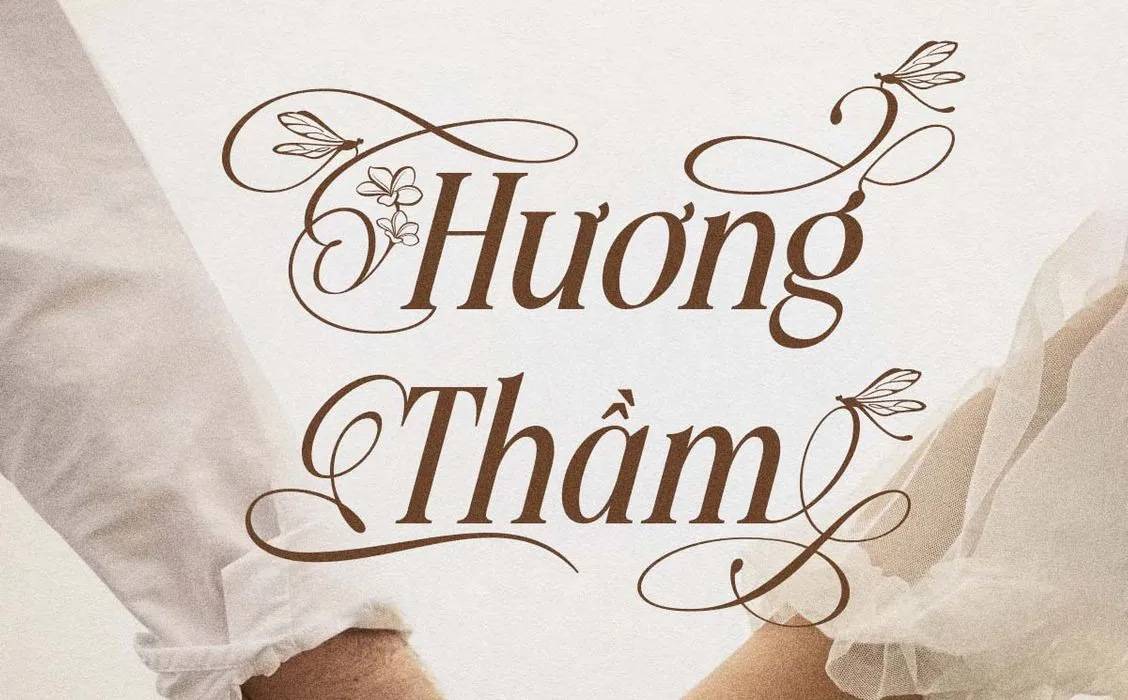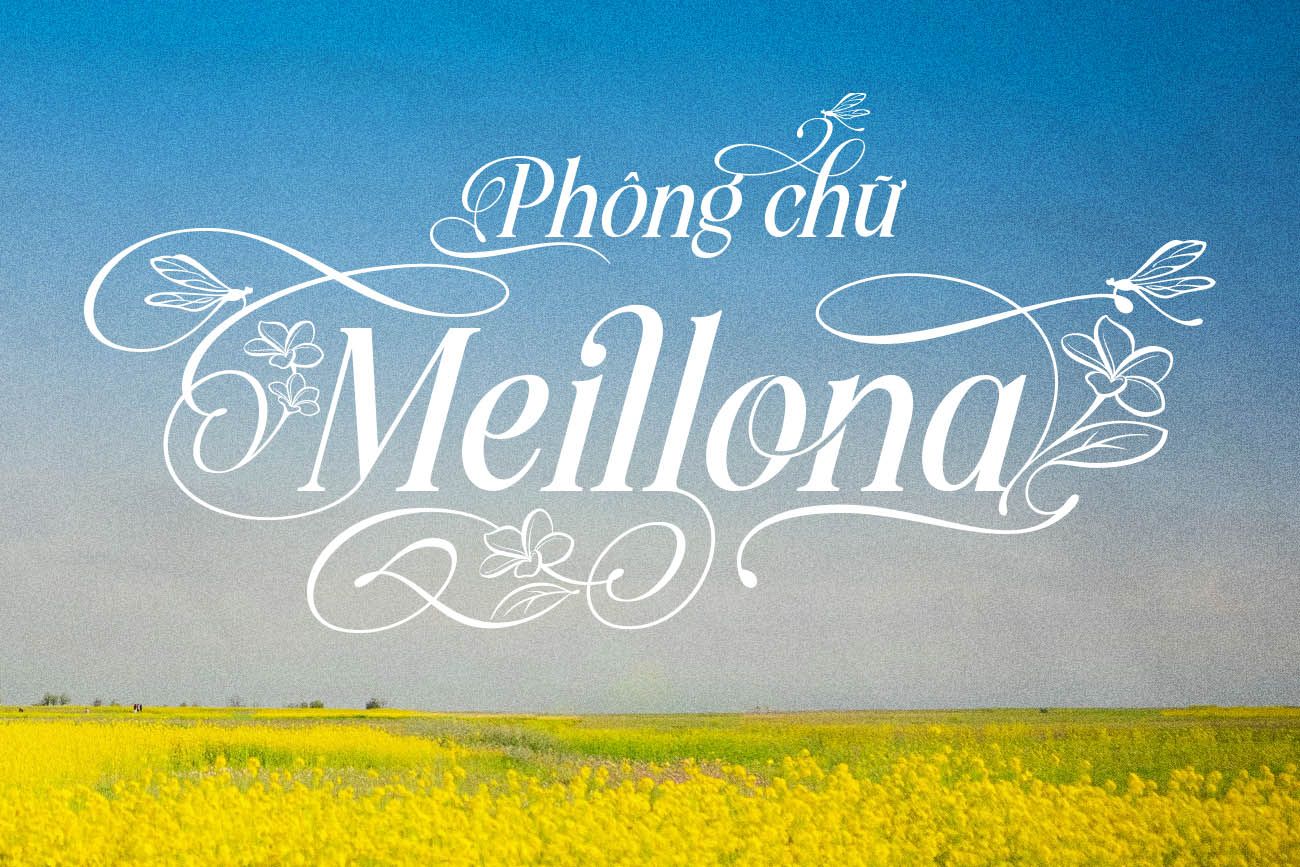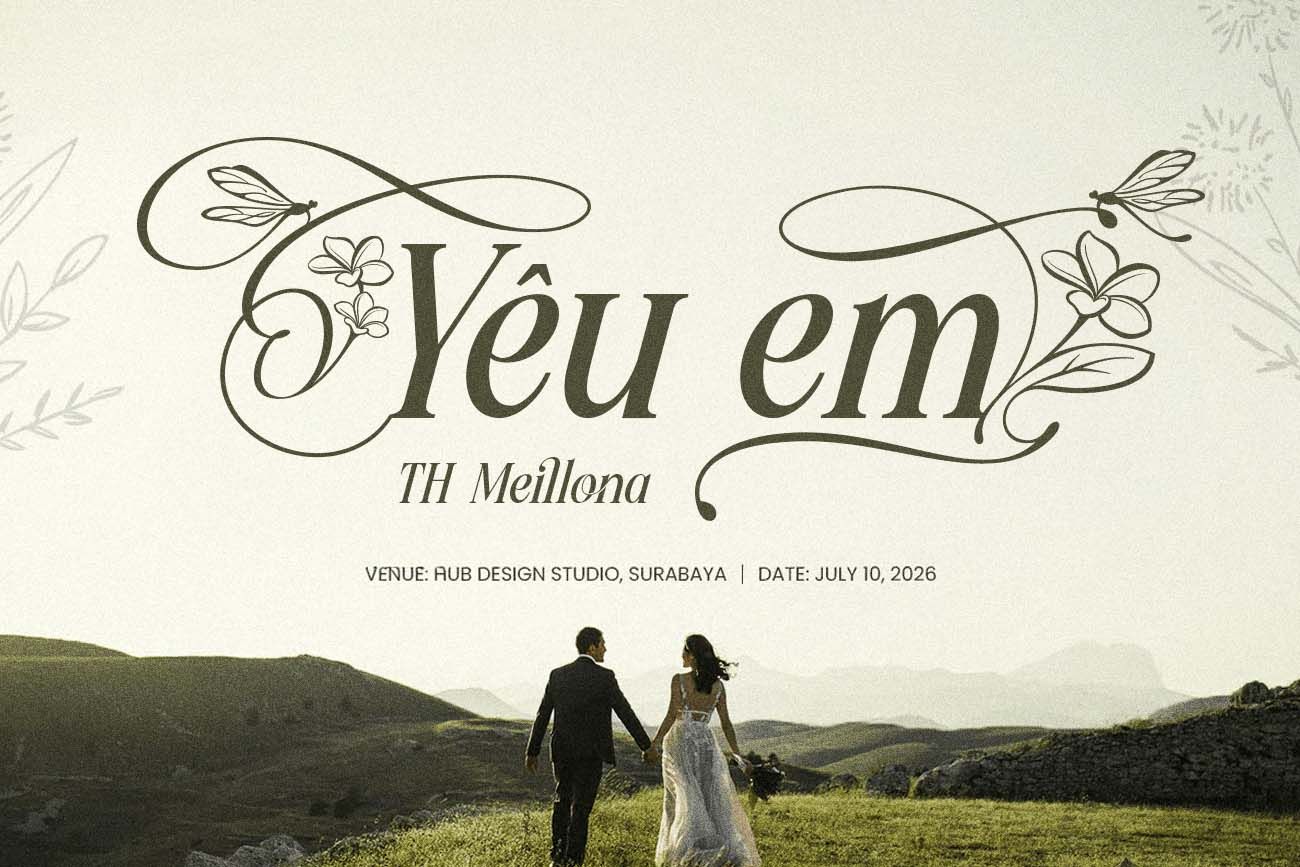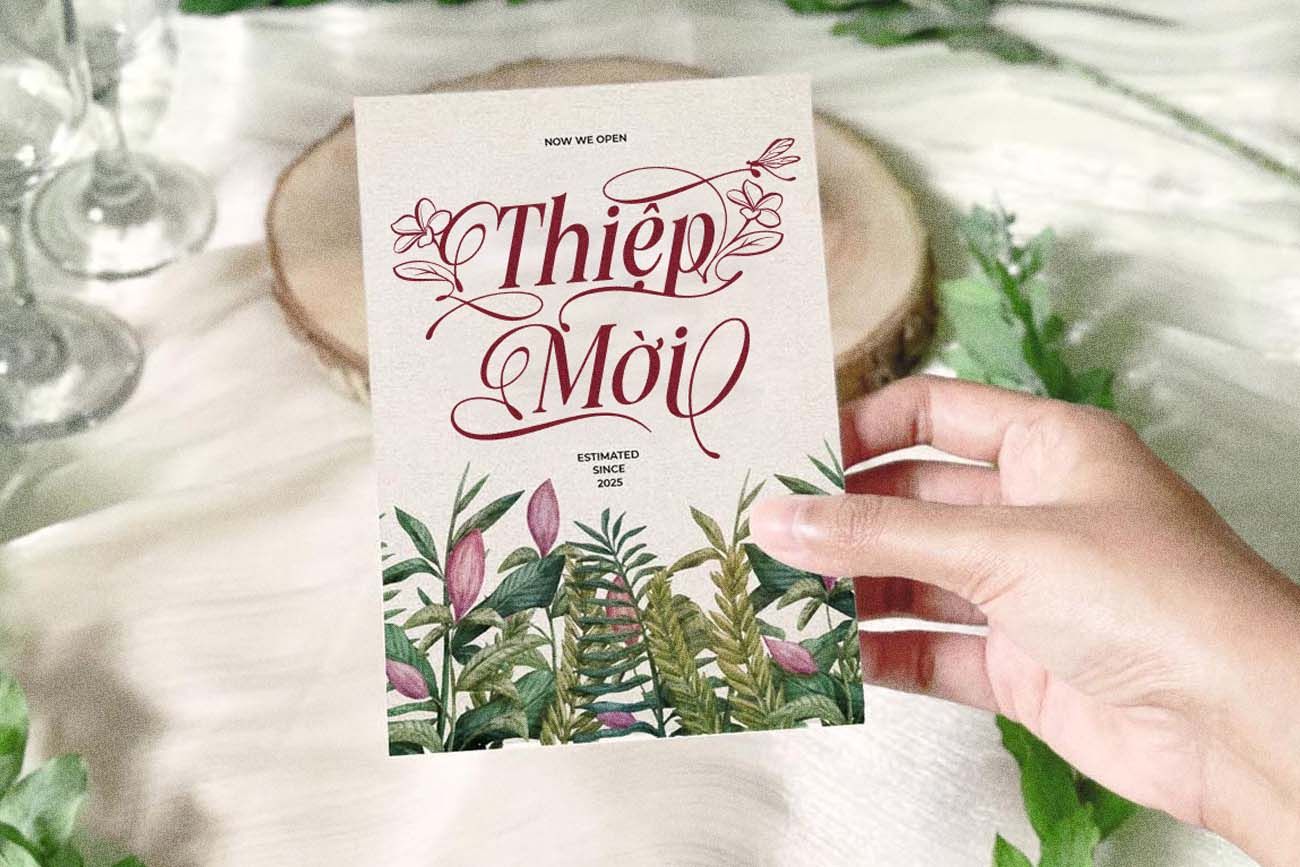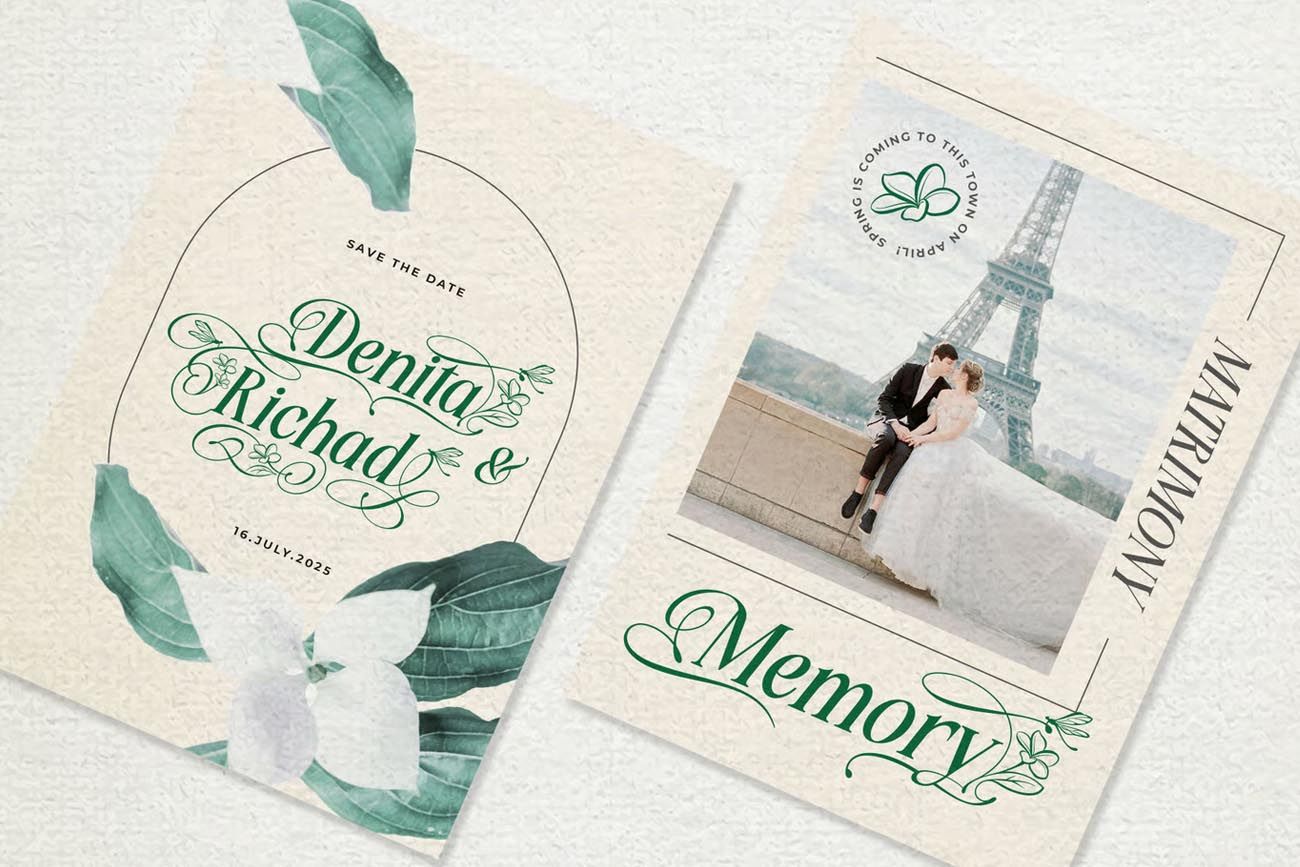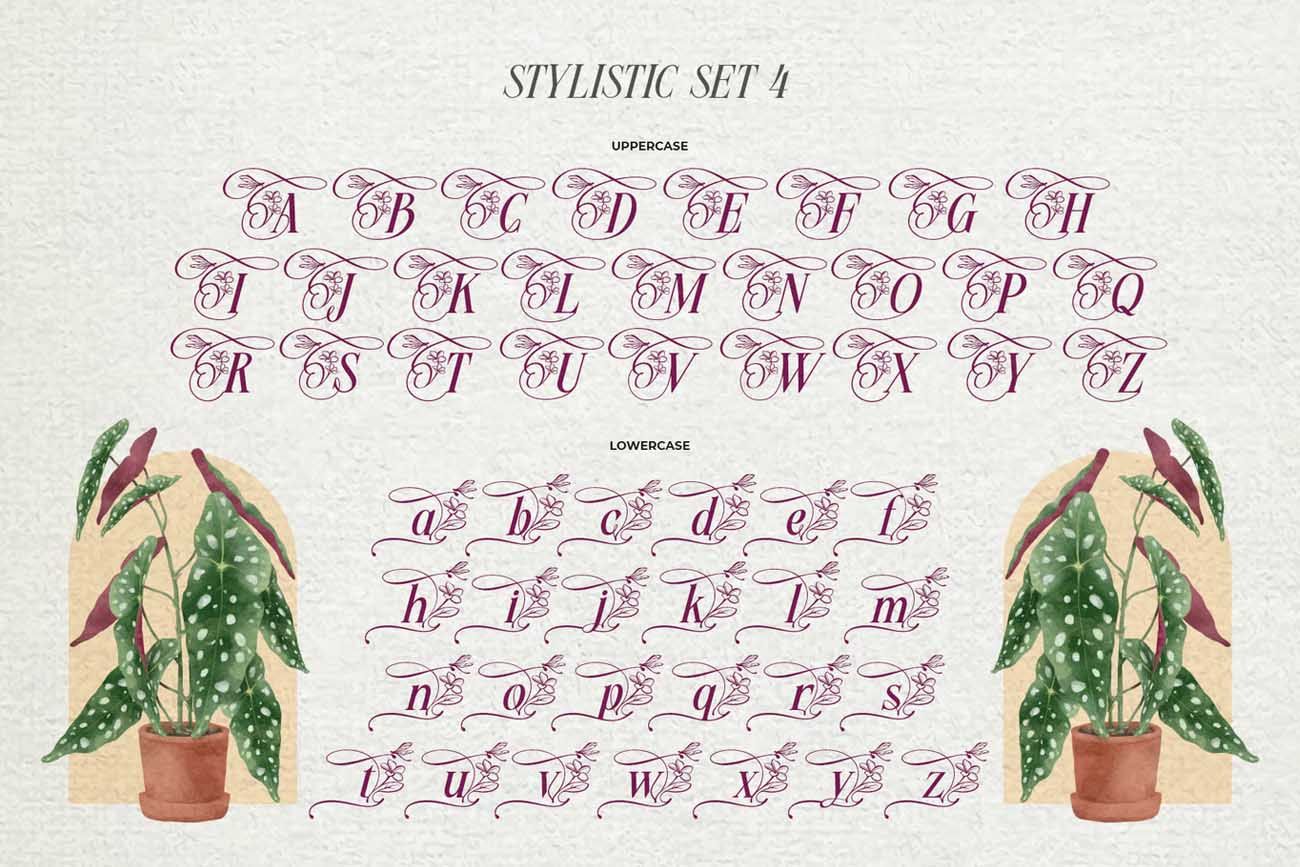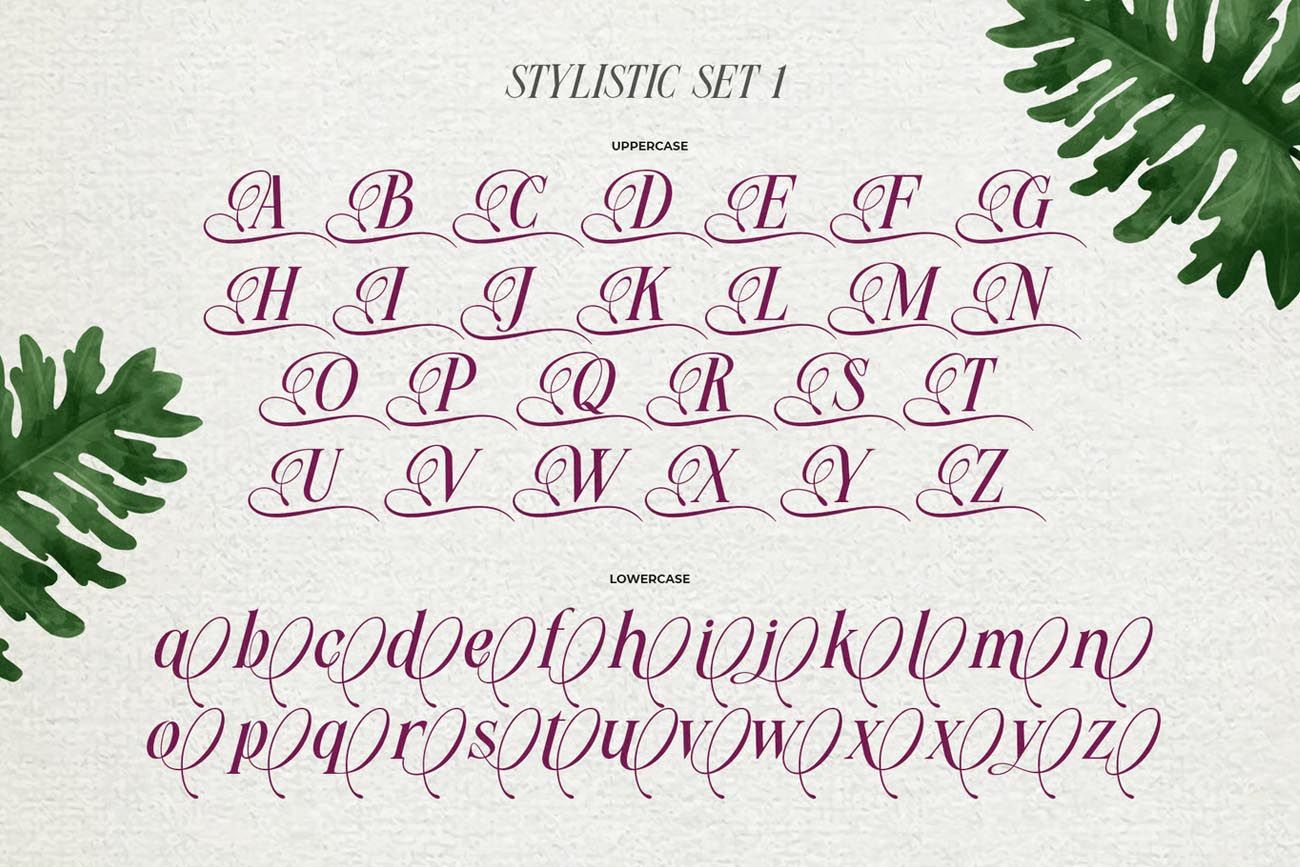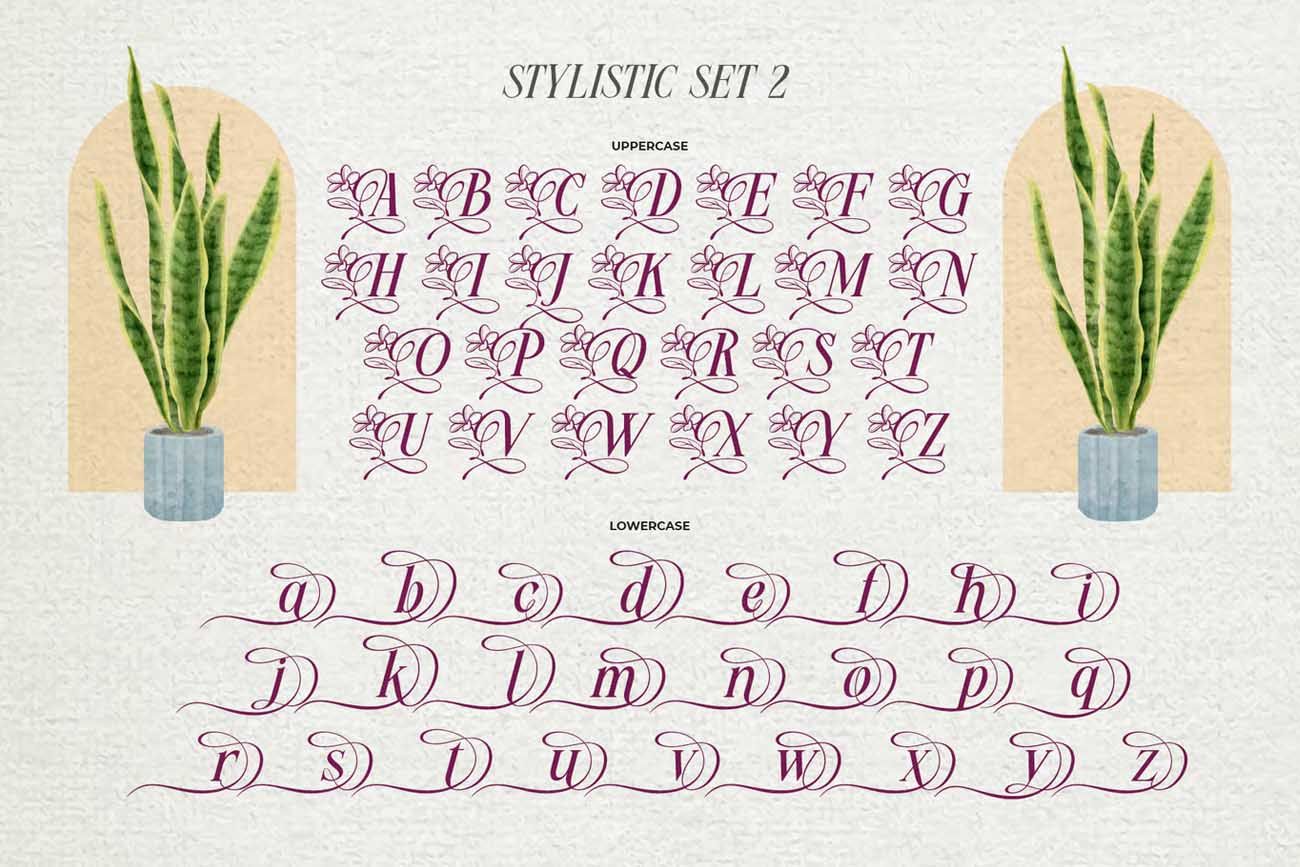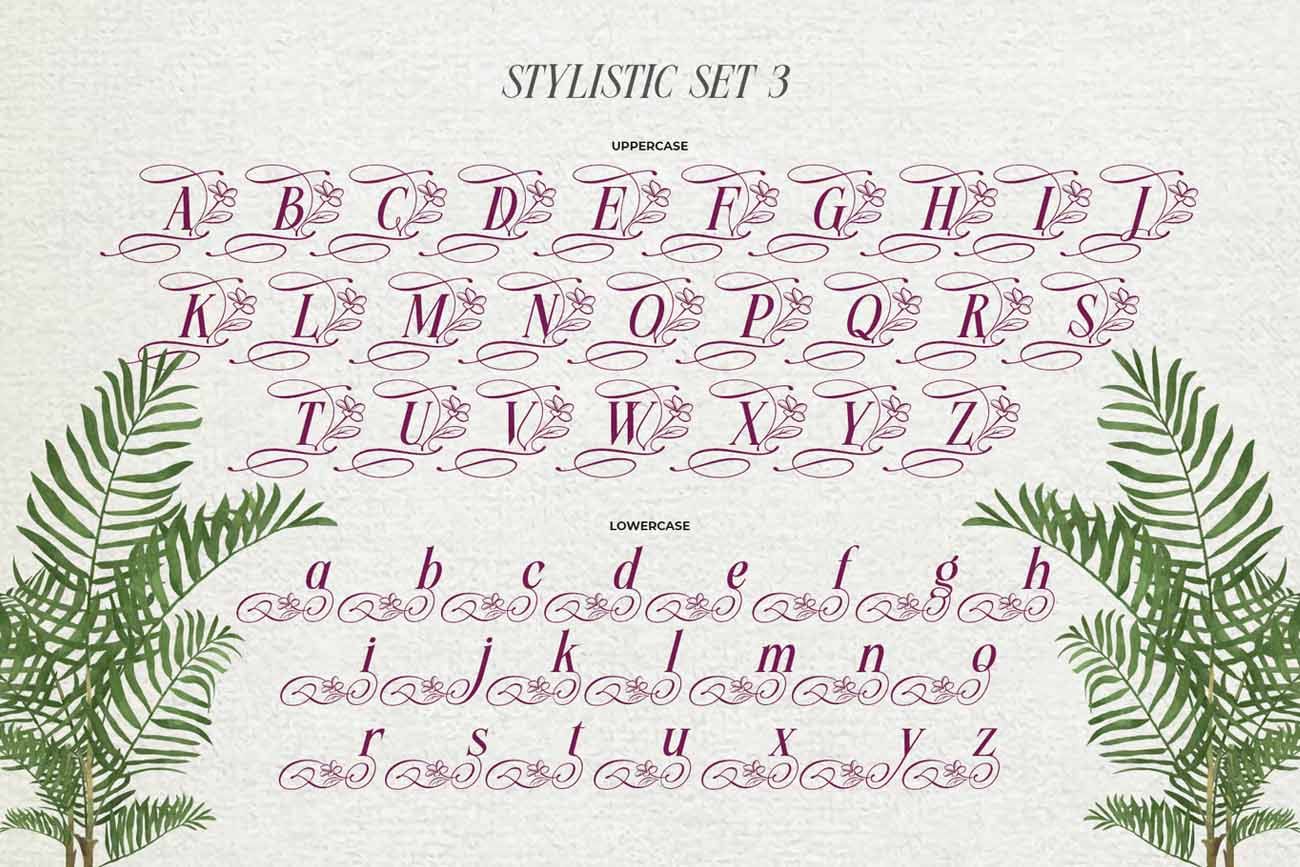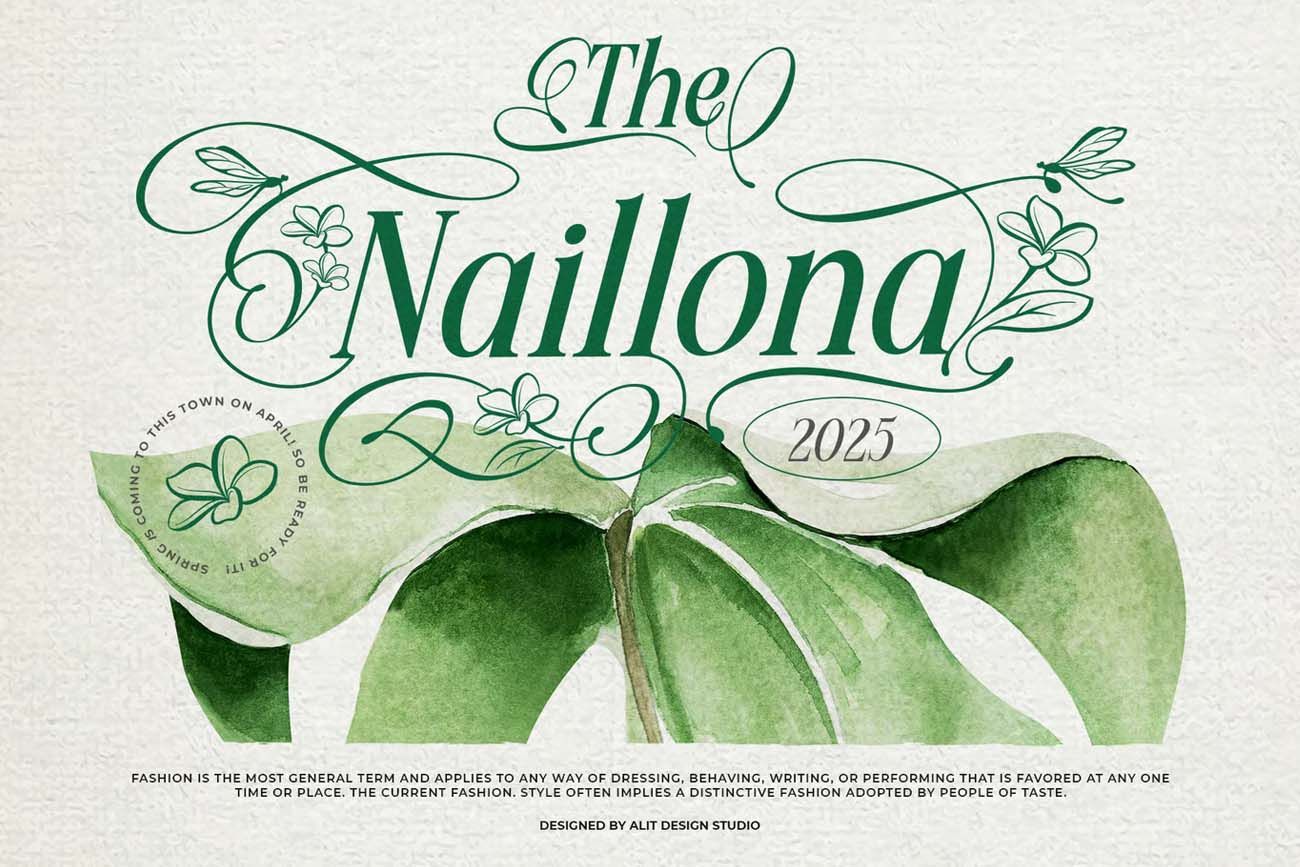
Trong thế giới thiết kế, một font chữ đẹp không chỉ đơn thuần là công cụ trình bày mà còn là “linh hồn” giúp truyền tải cảm xúc. Font chữ TH Meillona Việt hóa là một lựa chọn hoàn hảo dành cho những ai yêu thích sự lãng mạn, mềm mại nhưng vẫn sang trọng. Với những đường nét bay bổng, hoa văn tinh xảo, phông chữ này mang lại cảm giác nghệ thuật và phù hợp với nhiều phong cách sáng tạo khác nhau.
TH Meillona được phát triển từ font gốc Meillona, một sản phẩm nổi bật của Typetemp Studio, vốn nổi tiếng với nhiều thiết kế font chữ nghệ thuật. Phiên bản Việt hóa do Phạm Sơn thực hiện đã được tối ưu đầy đủ dấu tiếng Việt, chỉnh sửa kerning và giữ nguyên những chi tiết hoa lá mềm mại, đảm bảo người dùng có thể áp dụng dễ dàng trong nhiều dự án thiết kế mà không gặp lỗi ký tự. Đây chính là điểm cộng lớn giúp TH Meillona nhanh chóng được cộng đồng designer Việt Nam đón nhận.
Đặc điểm nổi bật của phông chữ TH Meillona Việt hóa là hệ thống stylistic alternates đa dạng, với hàng trăm glyphs, chữ hoa – chữ thường đều có thể biến hóa thành nhiều kiểu dáng khác nhau. Các đường flourishes mềm mại đi kèm họa tiết hoa lá, cánh bướm, mang đến sự uyển chuyển đầy nghệ thuật. Chính vì vậy, font chữ này đặc biệt phù hợp cho các dự án mang tính cá nhân hóa và cần sự sáng trọng, ví dụ như thiệp mời cưới, poster lãng mạn, typography nghệ thuật hay bộ nhận diện thương hiệu cao cấp.
Một điểm nổi bật khác chính là tính ứng dụng. Không chỉ gói gọn trong thiết kế thiệp cưới, TH Meillona Việt hóa còn có thể được sử dụng trong các dự án thiết kế logo, tiêu đề sách, bìa album, banner sự kiện, hay bất kỳ sản phẩm sáng tạo nào cần sự tinh tế. Với sự kết hợp hoàn hảo giữa nghệ thuật viết tay calligraphy và tính hiện đại, phông chữ này giúp tác phẩm của bạn nổi bật và ghi dấu ấn trong mắt người xem.
Font chữ TH Meillona Việt hóa không chỉ mang đến trải nghiệm thẩm mỹ mà còn là công cụ mạnh mẽ dành cho designer. Sự kết hợp giữa nguồn gốc quốc tế từ Typetemp Studio và tinh chỉnh Việt hóa bởi Phạm Sơn đã tạo nên một phông chữ hoàn thiện, vừa giữ được tinh thần sáng tạo của tác giả gốc vừa phù hợp tuyệt đối với ngôn ngữ Việt Nam. Nếu bạn đang tìm kiếm một font chữ viết tay nghệ thuật, sang trọng, đầy cảm xúc cho các dự án sắp tới, TH Meillona chắc chắn là sự lựa chọn đáng để tải về và sử dụng ngay.